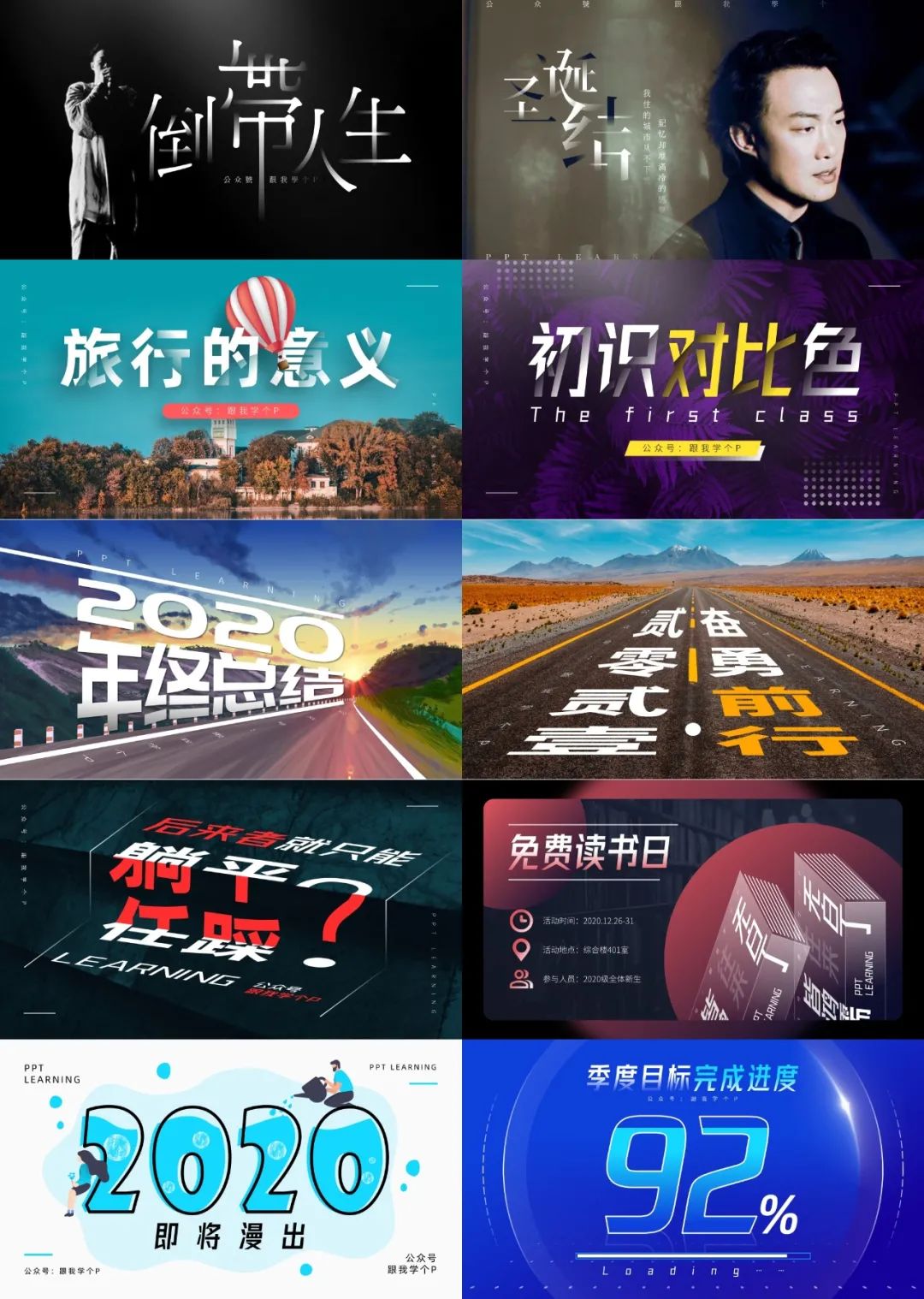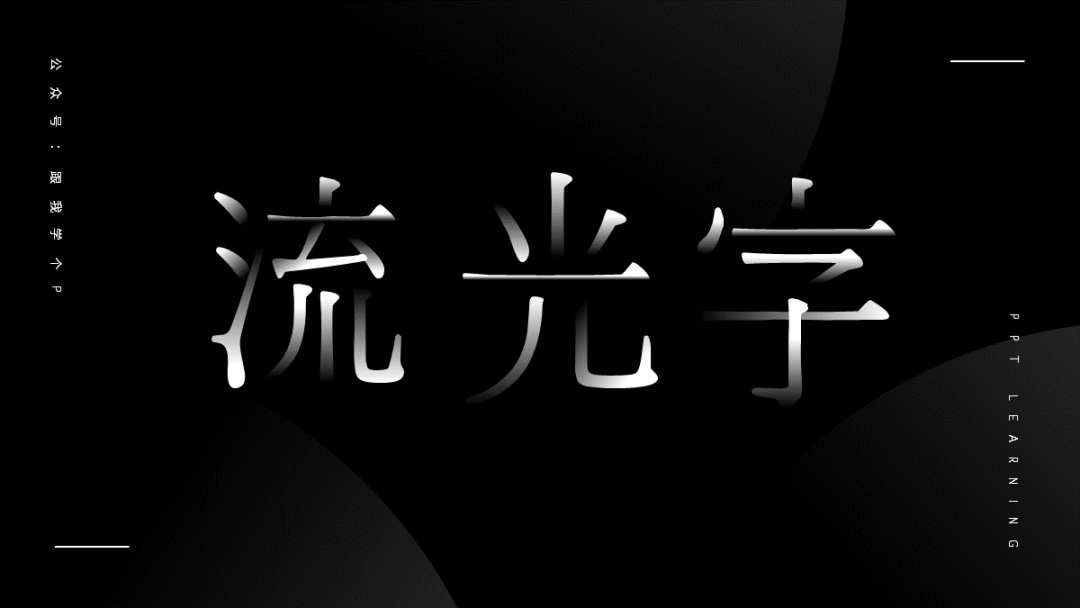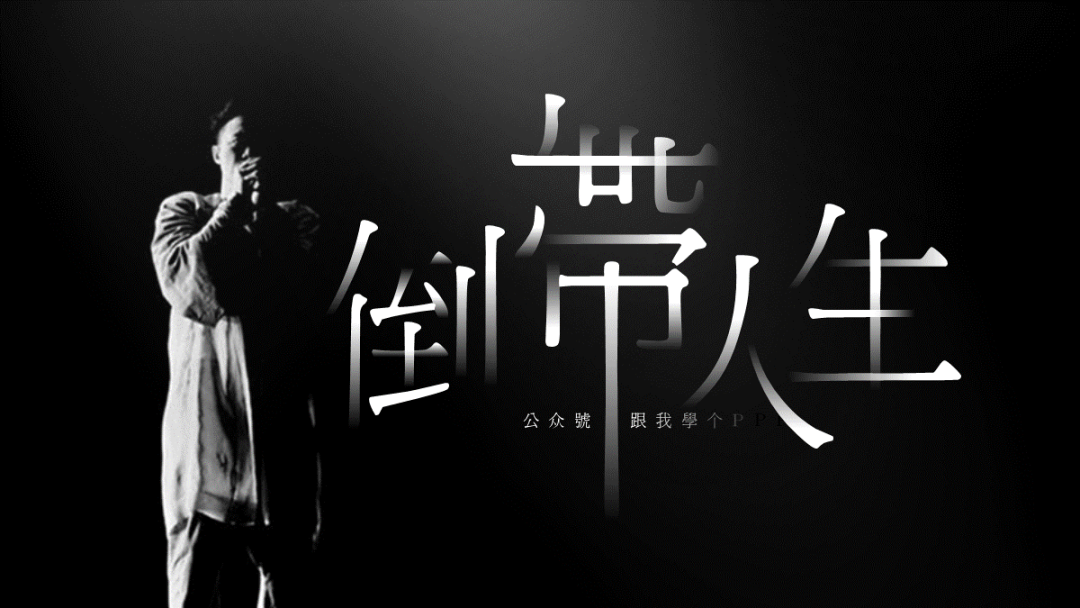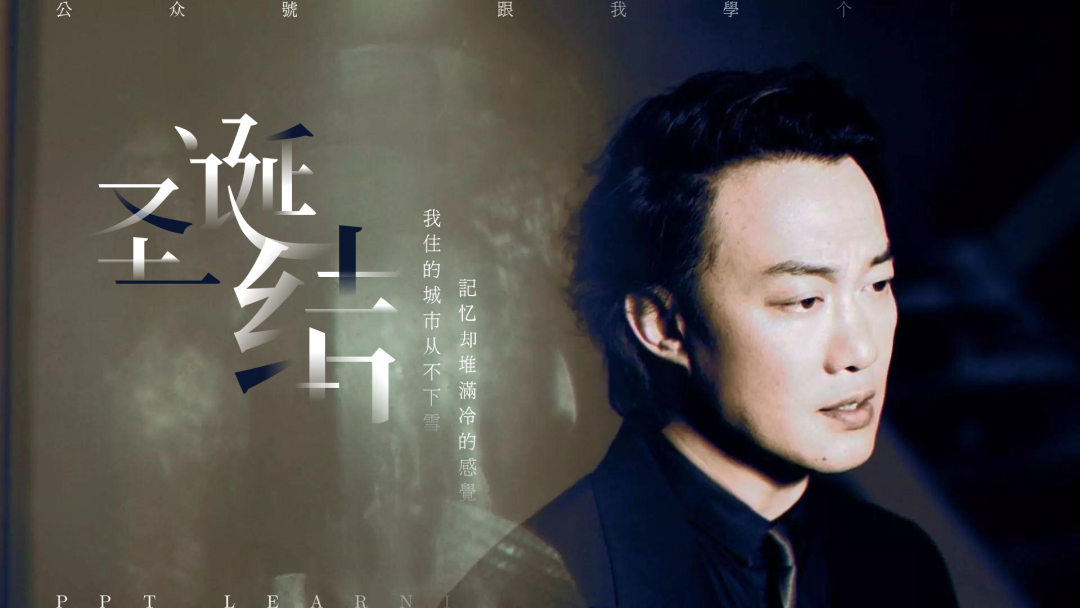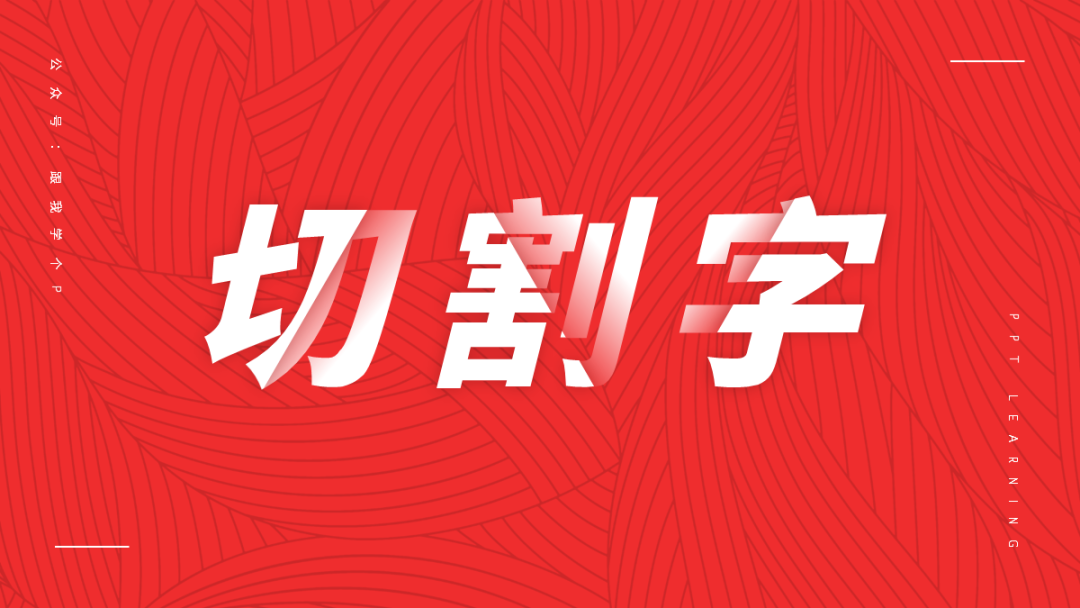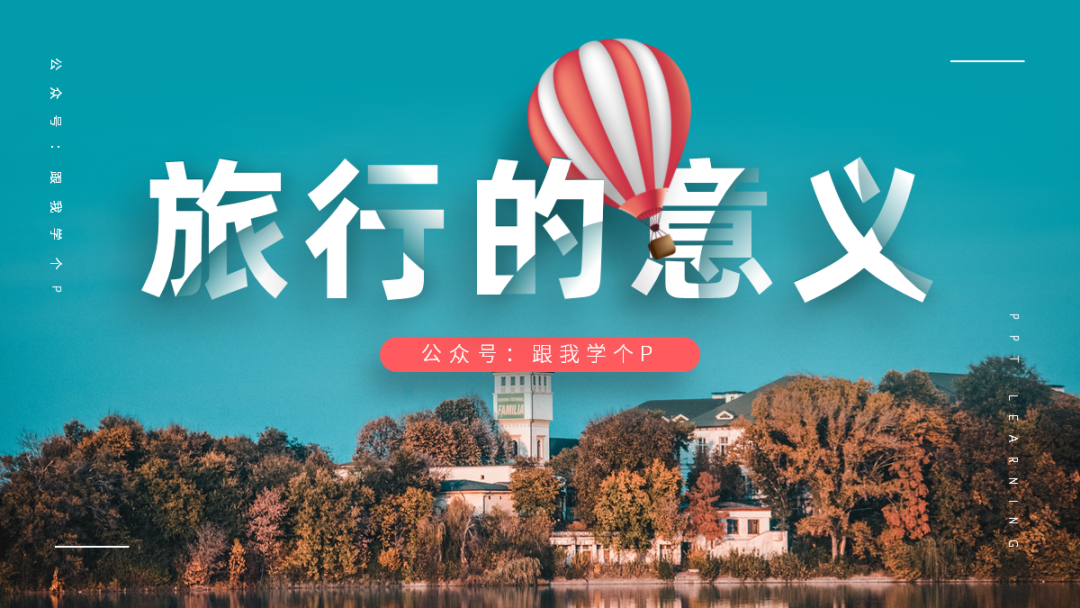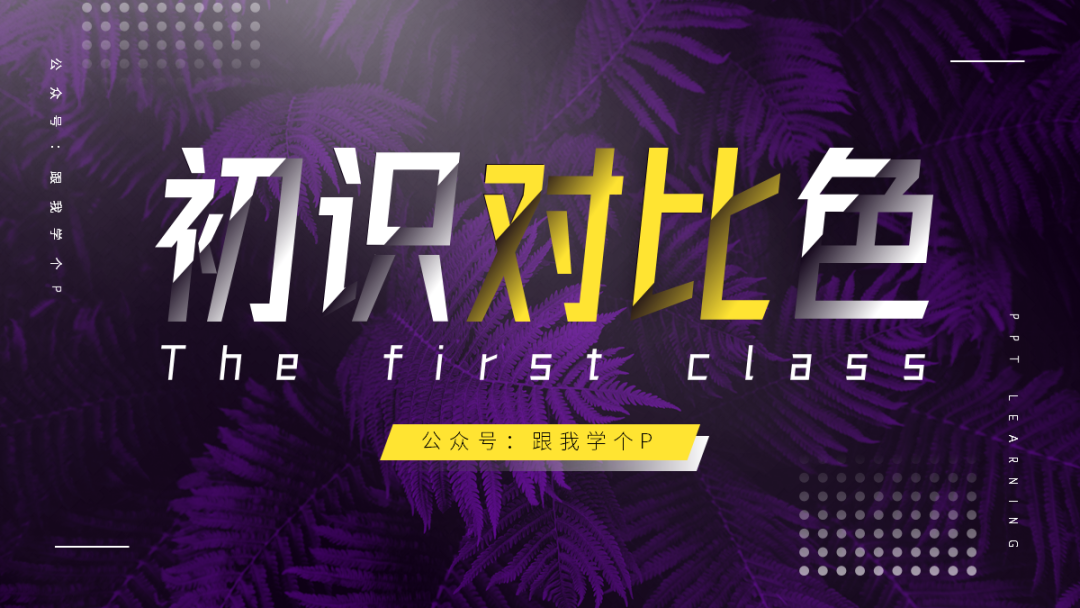
相比起排版跟配色,PPT中字体设计的地位就跟小三一样,不招人待见。but,一个好看的字效才是整页PPT的灵魂所在,如下图:
▼用了字效
(演示佛系体)
▼没用字效
知道重要性了吧!今天我就给你们安利5种字效,学多一种,头发多掉一把,工资多涨一分!
流光字效
流光字效是最有气质,也是最耗生发水的
,咱们先康康效果:
这种字效的制作,一共要用到三个PPT技巧:【合并形状、编辑顶点、设置渐变色】。
1)拆分笔画
先插入多个文本框并输入文字,摆放成下面这个样子:
接着,选中所有这些文本框,点击【形状格式】-【合并形状】-【拆分】,然后你就能看到大部分笔画都被拆出来了:
不过,有一些相连的笔画是拆不出来的。就像下面这个笔画,你得先右击笔画,点击【编辑顶点】,才能把它们拆成两部分:
具体操作方法见动图:
2)为笔画设置渐变色
把笔画全都拆出来以后,你就可以为它们设置渐变色了。
先选中所有笔画:
再随便右击其中一个笔画的边框,点击【设置形状格式】-【填充】-【渐变填充】:
【渐变光圈】只保留两个即可,并且其中一个光圈的【透明度】要设置为100%,这样你才能做出渐隐的渐变笔画:
这里需要提醒的是,由于每个笔画的走向都不同,因此渐变色的【方向】也要适时变化。
不过流光字效虽然好看,但是它一般只适用于文艺风格的PPT中,这是由它那该死的迷人的气质决定的。
切割字效
比起流光字,这种切割字效的性价比则高得多~因为特别容易出效果,而且风格百搭,大部分主题都能hold住!
如果取消这些字效,你会发现虽然页面也不会太差,只是缺了字效的点睛之笔,就显得有点平平无奇:
也就是说,当你觉得只放一行文字,页面太普通时,你就可以用这个方法,给文字加些亮点。
那么现在问题来了,这个切割字效是怎么做出来的?
你还是要用到熟悉的【合并形状】+【设置渐变色】功能。
1)切割文字
还是老规矩,插入多个文本框并输入文字,像下面这样排好版:
接着把所有文本框都复制一份出来,并将它们盖在原文本框上方,为了方便观察,我把新复制出来的文本框填充了黑色:
再插入几个形状(随便什么形状都可以),盖在你想要剪去的那部分文字上:
最后,按住【Ctrl】键,先选中文字,再选中形状(必须严格按照顺序选中),点击【形状格式】-【合并形状】-【剪除】:
然后你就能看到文字被形状剪掉了一部分:
接下来你要做的,就是为下方的那层文字设置渐变色。
2)设置渐变色
右击文本框,点击【设置形状格式】-【文本选项】-【文本填充】-【渐变填充】:
依旧只保留两个【渐变光圈】即可,至于这俩光圈的【颜色】,还有渐变的【方向】,你需要根据情况自己去鼓捣:
设置完成以后,你就可以看到文字变成这样了:
把盖在文字上的黑色形状改回白色,再用键盘上的方向键【←↑→↓】微调,让它们能完美盖住底部的渐变文字即可:
透视字效
在N年前我就做过一张下面这种图:
当时就有人问我这种【透视字效】是怎么做的,今天我就来回答了,并且给大伙儿做多了一张应景的案例:
你可以看到公路的图片跟透视字效的确很搭,制作方法也很简单,你只需要用到一个【文本转换】功能!
直接插入一个文本框并输入文字,接着点击【形状格式】-【文本效果】-【转换】-根据情况选择【淡出】或【梯形】效果即可:
选完了以后文本框就会发生形变了:
拉动文本框左上角的小黄点,你还可以调整文字的倾斜角度:
水位字效
你可以先把文字理解成一个透明的空瓶子,往这个瓶子里倒水的时候,你就能在外面看到水位上升,下面这个案例就很形象:
你可以用它来展示有关于“事项进度”的内容:
这种字效的制作方法也不难,你只需用到两个技巧:【设置文本轮廓】+【合并形状】功能。
1)制作线框文字
插入一个文本框并输入文字,接着把这个文本框复制多一个出来,放在一边先不用管它:
接着随便右击其中一个文本框,点击【设置形状格式】-【文本选项】-【文本填充】-【无填充】-【文本轮廓】-【实线】,再设置好线框的粗细跟颜色:
然后你就能看到普通的文字变成了镂空的线框文字:
2)剪除文字
现在你只需插入一个PPT自带的“波浪”形状,盖在刚刚复制出来的那个文本框上方:
利用【合并形状】里的【剪除】功能,剪掉这个文字,最终得到以下效果:
把线框文字【置于顶层】,盖在被剪除过的文字上方,搞定!
折叠字效
如果说第一个【流光字效】制作起来麻烦程度有80分,那么这个【折叠字效】至少有200分…但实用程度却可能只有20分…
所以比较适合用来做海报,先康康两个案例:
阶梯跟书本上的字效,都算是折叠字,只不过一个是作为文案主体,另一个则作为了图案装饰物出现。
这种字效的制作需要用到的技巧有两个,分别是:【合并形状】、【三维旋转】功能。
1)拆分文字
首先,先插入一个文本框并输入文字,再复制多两个出来:
在这三个文本框上面,分别盖上三个矩形,注意矩形的上下边缘之间一定要对齐,如红线所示:
接着,我们先对第一个文字进行以下操作。
按住【Ctrl】键,先选中文本框,再选中它上面的形状,点击【形状格式】-【合并形状】-【相交】:
最终得到文字与形状相交的部分:
为剩下两个文本框进行同样的操作,最终得到如下效果:
把这三部分拼接起来,就能形成一个完整的文字了:
2)为文字设置三维旋转
你可以借助【三维旋转】这个功能,把二维的东西旋转出三维的效果:
【三维旋转】里有【预设】功能。
你可以一键将一个普通的矩形旋转出下面这些角度:
而且这些预设的角度之间还存在某种关联,比如你可以把这些旋转过后的矩形拼成一个立方体:
也就是说,如果我们现在把刚刚拆分出来的那些文字也按照同样的方法旋转,那你也可以拼出这些特殊的角度:
你可能还会问一个问题:如果我在拼接完文字以后想修改文字的旋转角度怎么办?
很简单,直接点击【三维旋转】功能旁边的【向上/下/左/右/前/后旋转】这六个按钮,即可微调旋转的角度:
旋转完了以后要是发现文字都变形了,那也不慌,选中文字,手动按键盘上的方向键【←↑→↓】,可以微调文字的位置。
好了,这最后一个字效的制作方法也交代完了,仰天长舒一口气!乌黑秀发落满地!
▎总结
现在我们再来回顾一下以上字效,以及它们的适用场景:
流光字效:适用于文艺风格PPT中,实用性一般,制作麻烦;
切割字效:风格百搭,实用性强,制作超简单; -
水位字效:风格百搭,实用性一般,制作有点麻烦; -
透视字效:风格百搭,实用性强,制作简单; -
折叠字效:只适用于特定页面的制作,实用性差,制作巨麻烦;